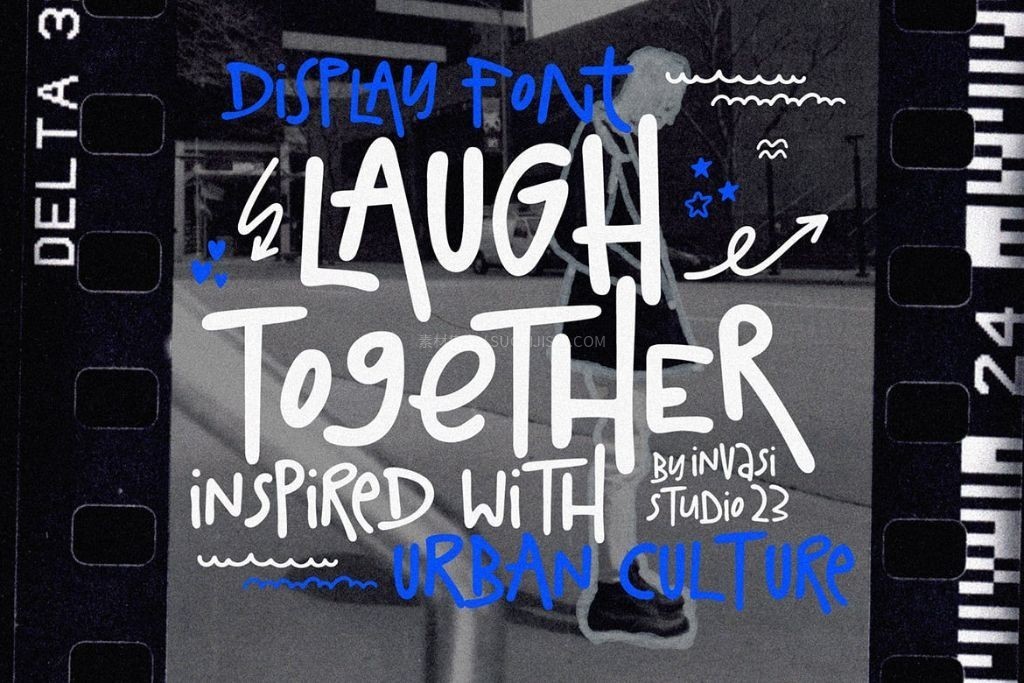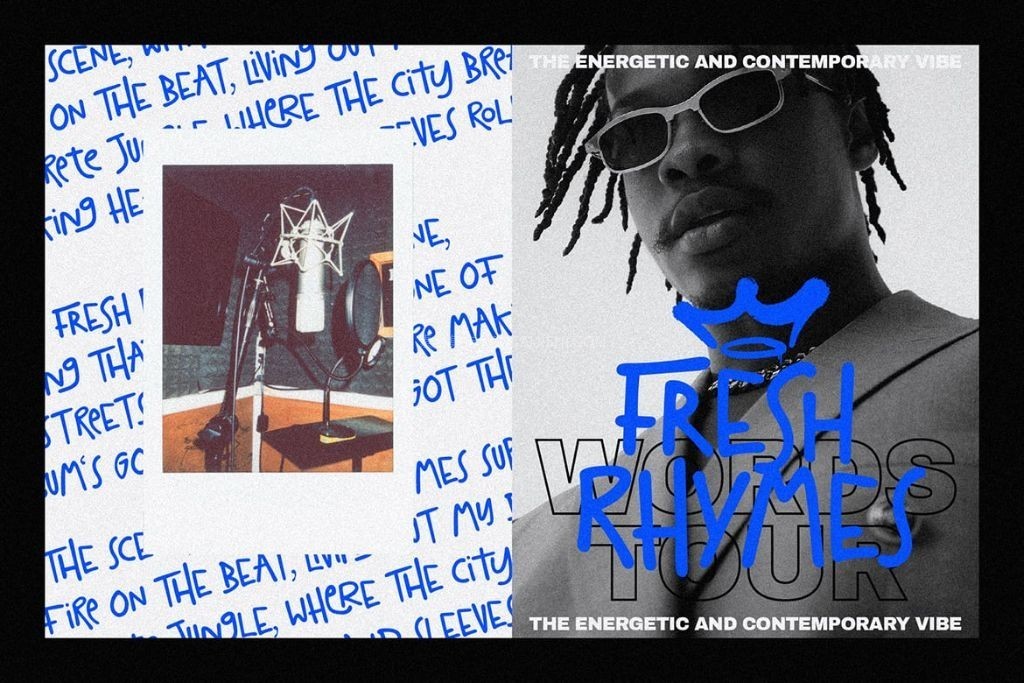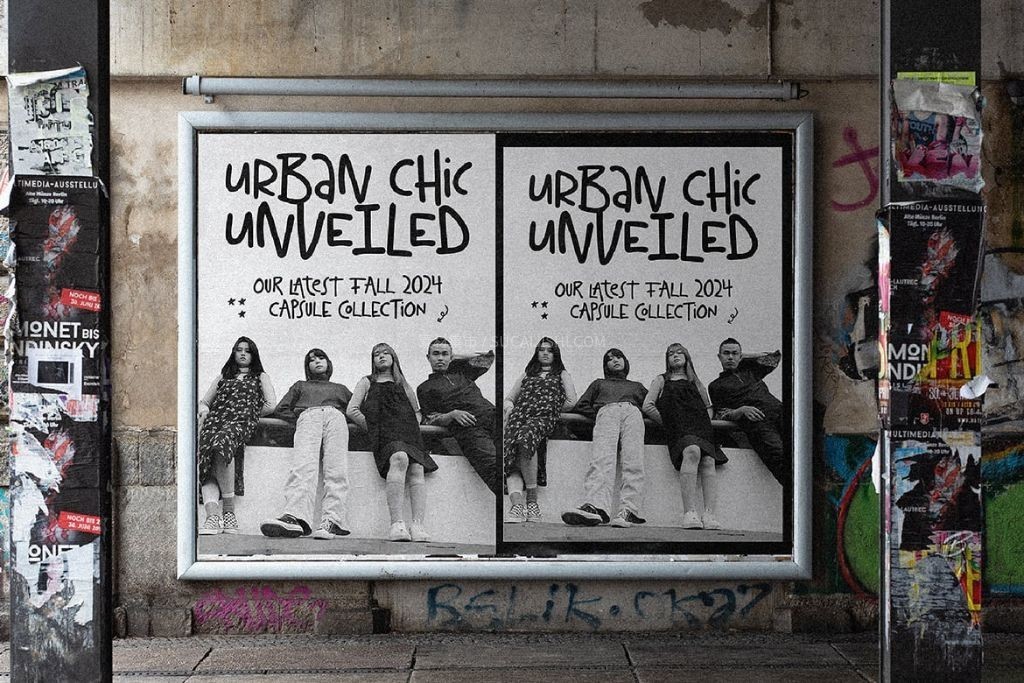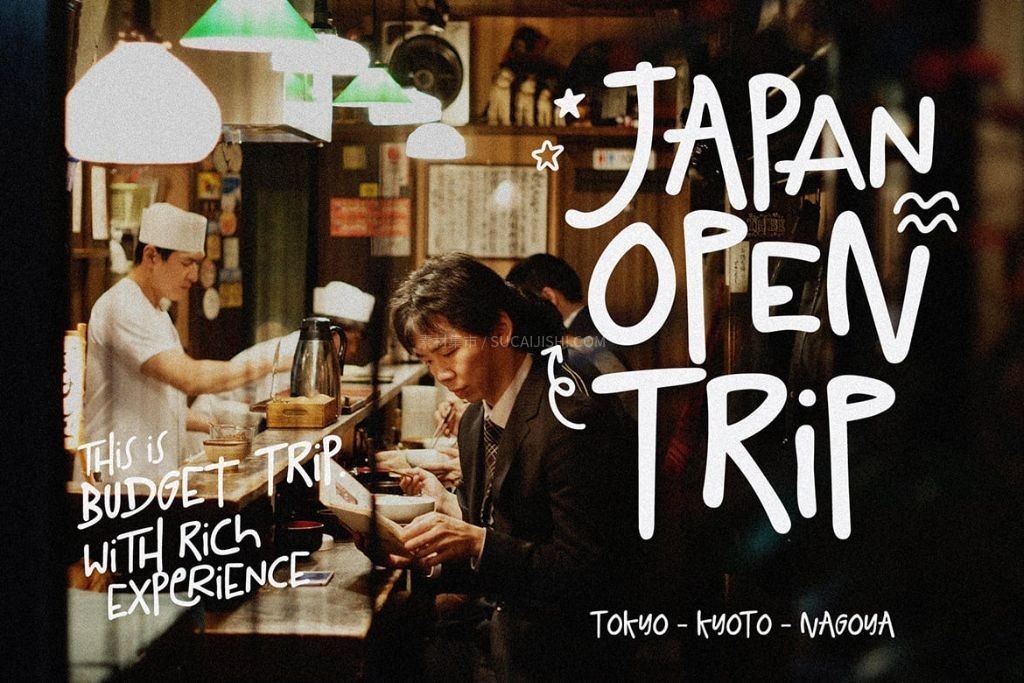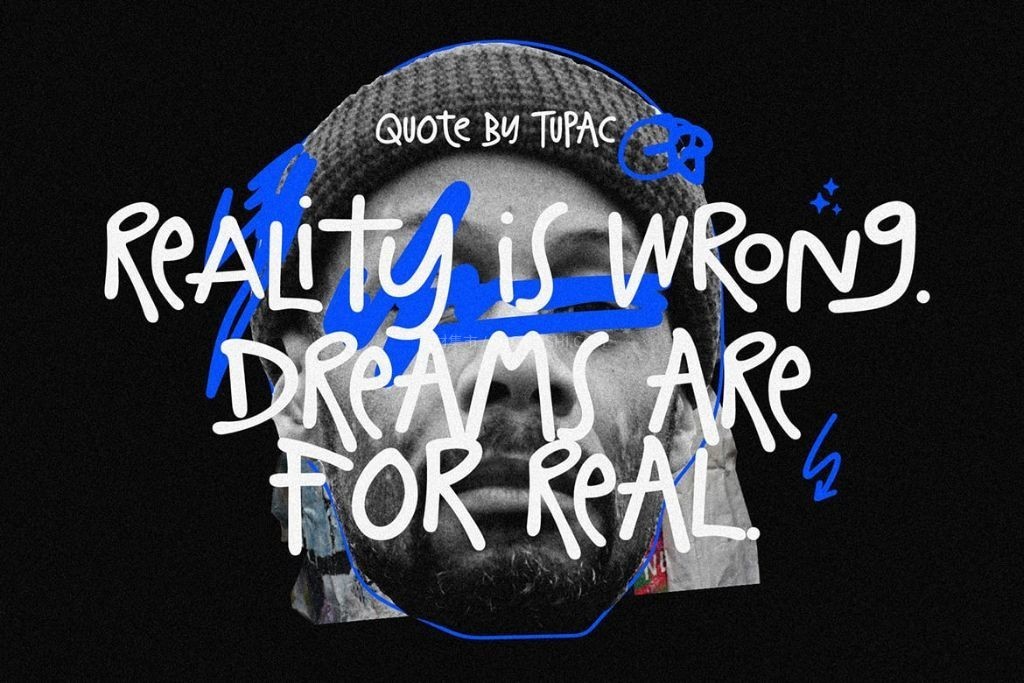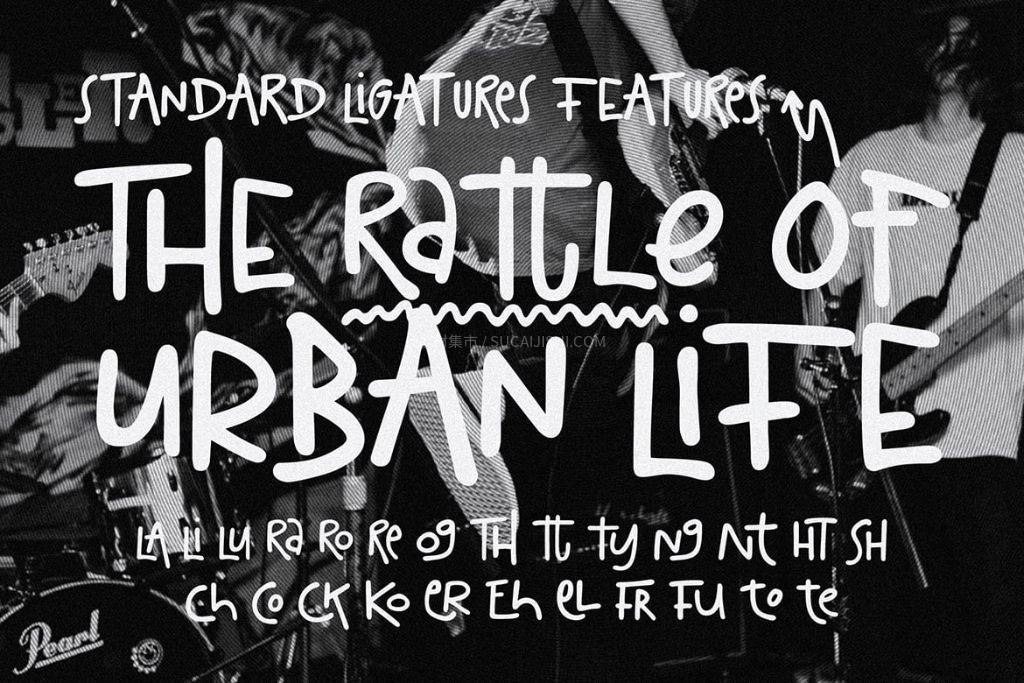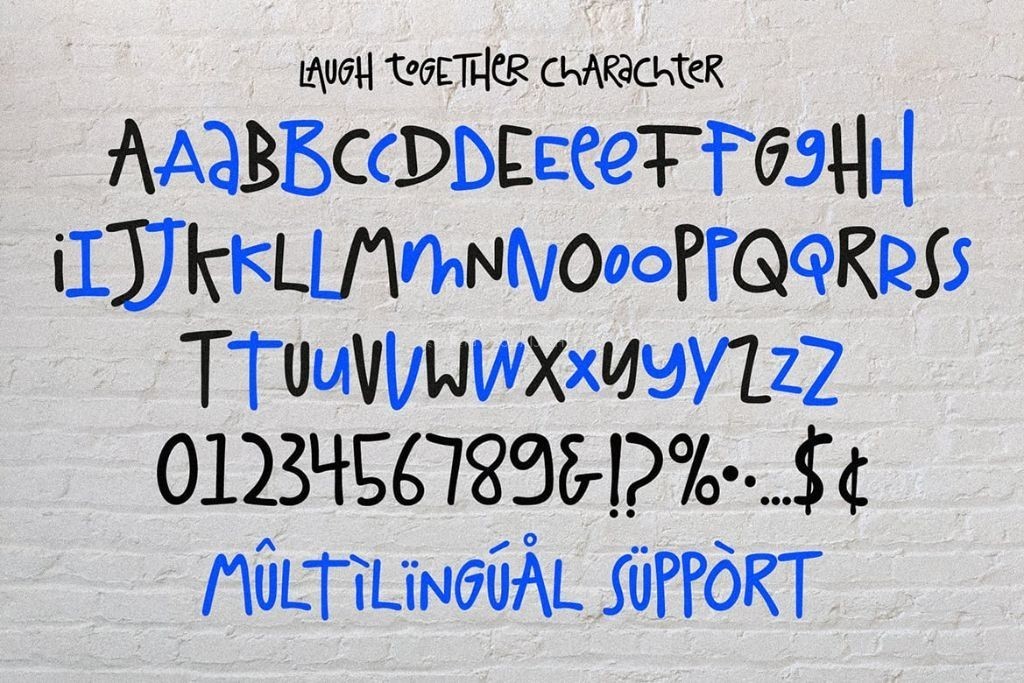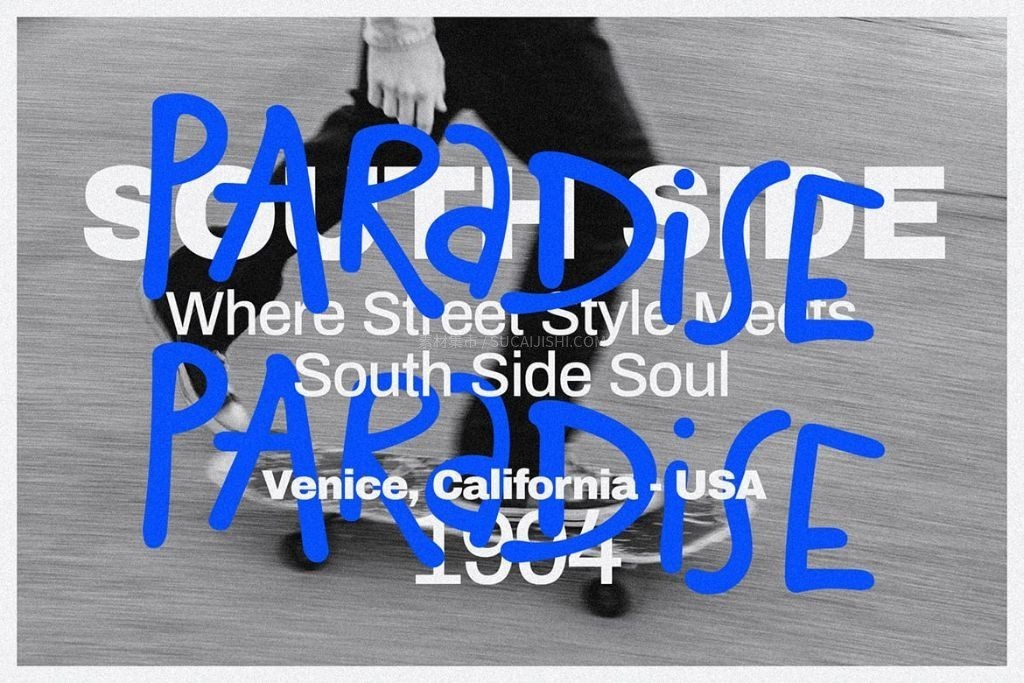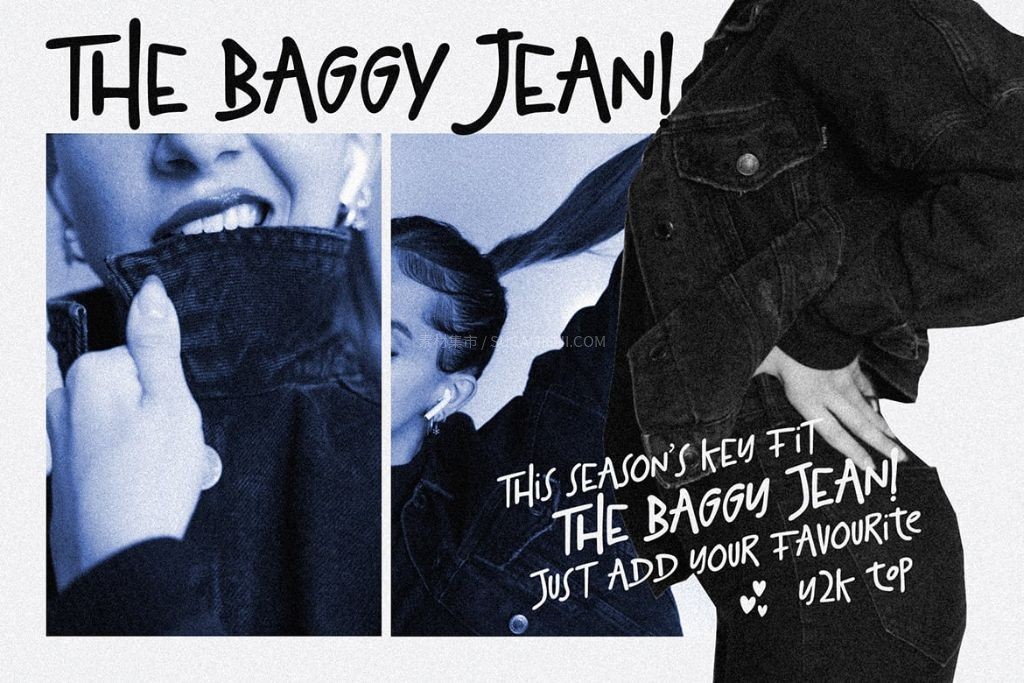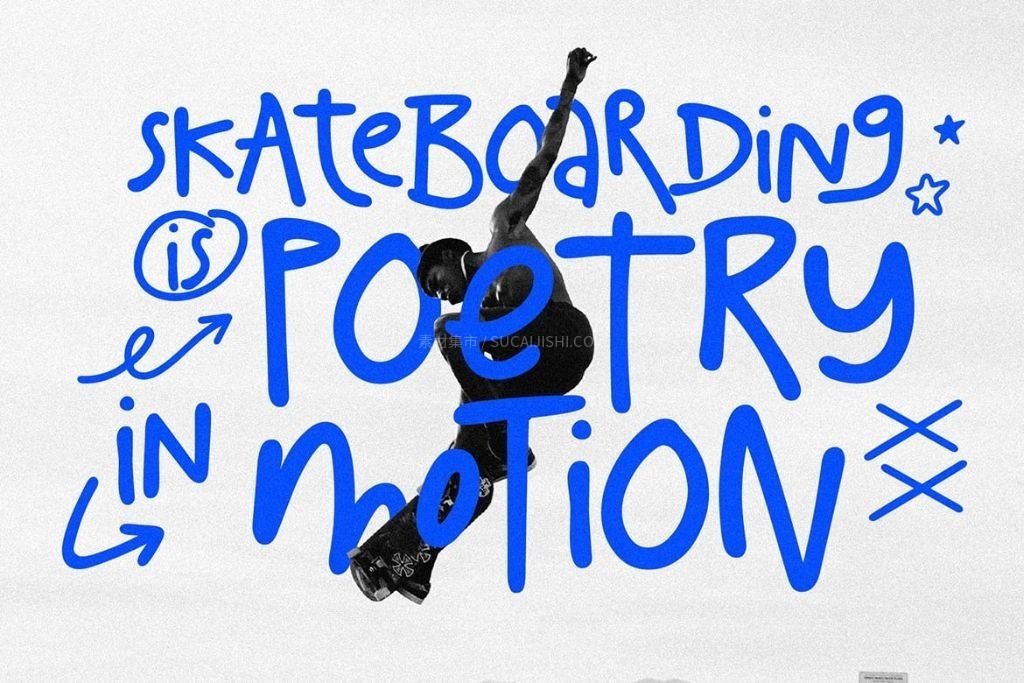
Laugh Together活力涂鸦手写字体
Laugh Together 是一款深度致敬都市街头服饰文化与缤纷涂鸦艺术的展示字体。其大胆且极具表现力的线条,能瞬间为您的设计注入鲜活的趣味与叛逆的个性。本字体采用全大写设计,特别内置了 A-Z 完整的替代字符集,让您可以像街头艺术家一样自由组合,创造出绝不重样的视觉效果。